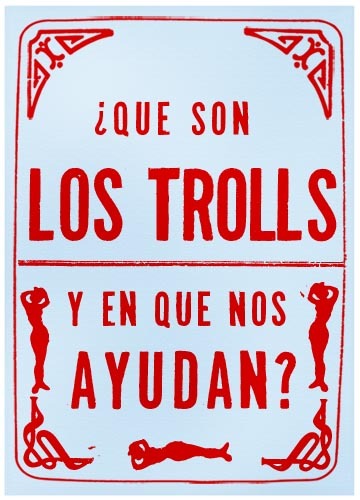
Mal de Ojo von Tim Gibbon ist eine kostenlose, abgenutzte Display-Schrift mit der rohen Wucht handgetuschter Plakatbuchstaben. Die Zeichen sind hoch, schwer und an den Kanten rau, mit einer trockenen, abgenutzten Textur, die der gesamten Schrift einen zerkratzten, gestempelten und leicht bedrohlichen Charakter verleiht.
Dieses raue Flair passt perfekt zu Musik-Flyern, Horror-Titeln, Fanzine-Covern, Bar-Postern und auffälligen Verpackungen, bei denen eine kostenlose Schrift nicht makellos, sondern roh wirken soll. Sie eignet sich zudem hervorragend für kurze Schlagzeilen und Monogramme, da die Großbuchstaben trotz der distanzierten Oberfläche eine solide, blockartige Silhouette behalten.
Text und Bilder wurden von im Buchdruck hergestellten spirituellen Botanik-Flugblättern aus Oaxaca, Mexiko, gescannt. „Mal de ojo“ bedeutet „böser Blick“.